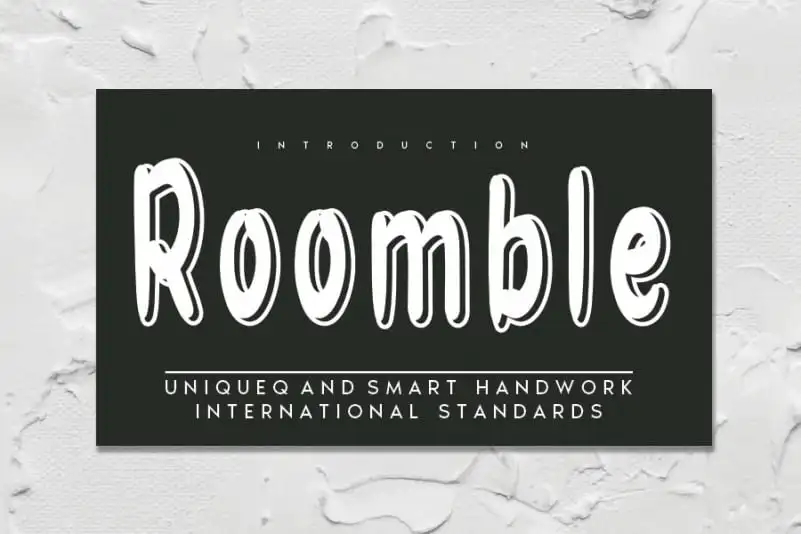
Roomble Display Font – Download Grátis
A Roomble Display Font é uma elegante fonte escrita à mão que carrega consigo a simplicidade do dia a dia, com seus traços leves e sua personalidade única. Seu estilo natural e único faz dela uma escolha perfeita para um amplo gama de projetos gráficos. Percebendo os limites da imaginação, seu designer, andikastudio, criou algo verdadeiramente amigável e suave para se integrar em qualquer design concebido pelos mais diversos talentosos artistas. Seja você um jovem designer ou um artista de renome, a Roomble Display Font é uma fonte escrita à mão que não apenas oferece um toque natural à sua criação, mas também estimula seu pensamento criativo e imaginação. Aqui está uma fonte capaz de criar trabalhos únicos e inspiradores, disponível para quem quer explorar ainda mais a arte da design grafico.